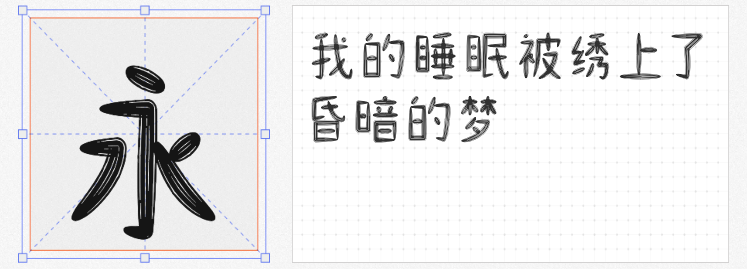
在视觉设计领域,字体是传递品牌调性的无声语言。本文精选四款兼具艺术性与实用性的免费商用字体,覆盖科技、国风、趣味等多元场景,助力设计师打造独特视觉表达。
1. 斗鱼追光体2.0
由斗鱼武汉研发部UED团队主导设计,这款字体以“锐利棱角+流畅弧线”的矛盾美学,诠释直播平台的年轻张力。倾斜的笔画角度与去圆角处理,暗喻“追光者”的进取姿态,中宫紧凑的结构强化视觉凝聚力。适用于游戏直播海报、科技产品标题等场景,轻松传递品牌“活力、娱乐、科技”的核心特质。
2. 阿里妈妈刀隶体
基于《爨宝子碑》的AI算法重构,这款字体以“刀刻斧凿”般的笔触重塑隶书风骨。三角点折的锐利转折与横画“雁尾”的夸张收笔,形成强烈的视觉冲突;非常规的布白设计打破均衡美学,在“险”与“正”的博弈中展现东方哲思。推荐用于文化创意类海报、国潮包装设计,为作品注入古朴稚拙的艺术张力。
3. 阿里妈妈东方大楷
通过机器学习颜真卿《多宝塔碑》的笔法精髓,这款字体在数字化重构中保留了“丰腴厚重”的颜体特征。算法精准捕捉落笔时的顿挫节奏与藏锋护尾的书写韵律,使横细竖粗的骨架更具呼吸感。适用于传统文化宣传、高端品牌标题等场景,让现代设计承载千年书道之美。
4. 山字瓜子体
设计师frankleng从瓜子形态中汲取灵感,创造出这款“胖嘟嘟”的创意字体。圆润的笔画末端与不对称的笔画粗细,营造出孩童涂鸦般的稚拙趣味。作为标题字体时,其夸张的视觉表现力能瞬间抓住眼球,但需注意避免小字号使用。推荐用于儿童品牌、甜品店招牌等轻松场景,为设计注入治愈系能量。